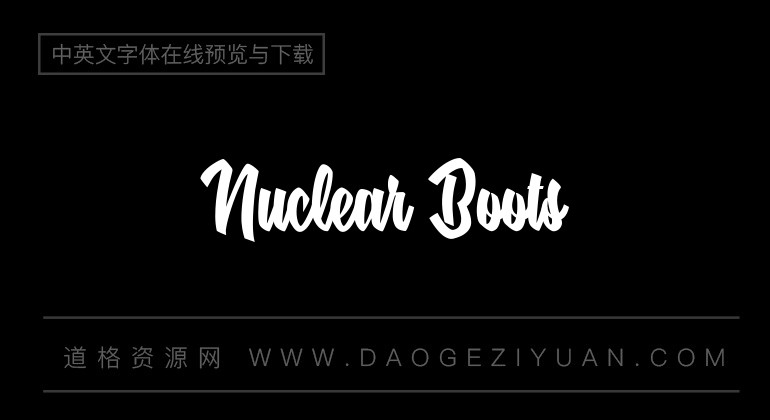
Nuclear Boots是一种流行的免费字体,由Scott Simpson创造。它的设计灵感来自于20世纪50年代的广告和宣传海报,具有明显的复古风格。 Nuclear Boots字体的特点是粗大的笔画和强烈的对比度,同时还具有一些衬线字体的属性,使其易于阅读和识别。 它的字形设计非常独特,包括许多自定义字母形状。 Nuclear Boots字体可用于各种用途,如海报设计、标识、包装设计和印刷品等。它提供了多种不同的字重和样式,可以满足不同设计需求。除了免费提供TrueType字体格式之外,该字体还提供了Web字体格式,方便在网页设计中使用。 总之,Nuclear Boots字体是一款非常有创意和个性的字体,适用于各种设计场景,非常值得一试。内容介绍
Nuclear Boots是一款非常不错的手写艺术字体,具有很好的视觉感,适合于文化类的宣传设计、商业类品牌的广告和产品包装设计以及个性化文字排版等较多场景。